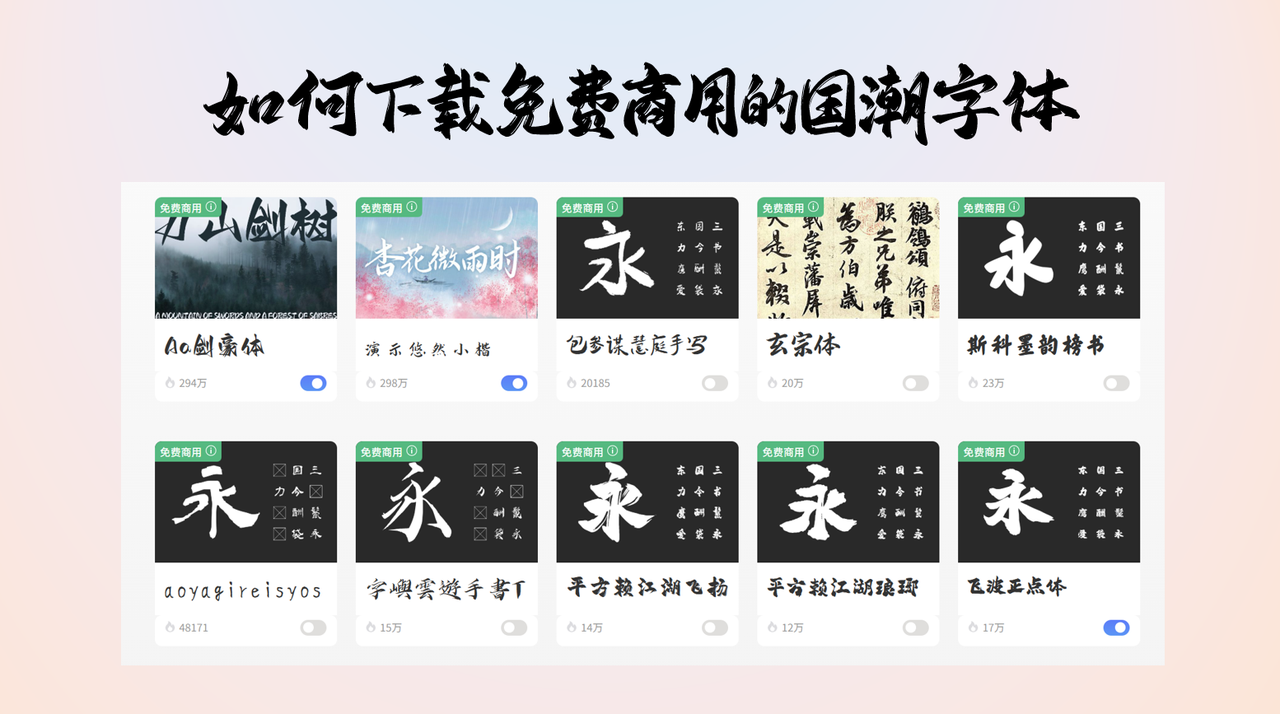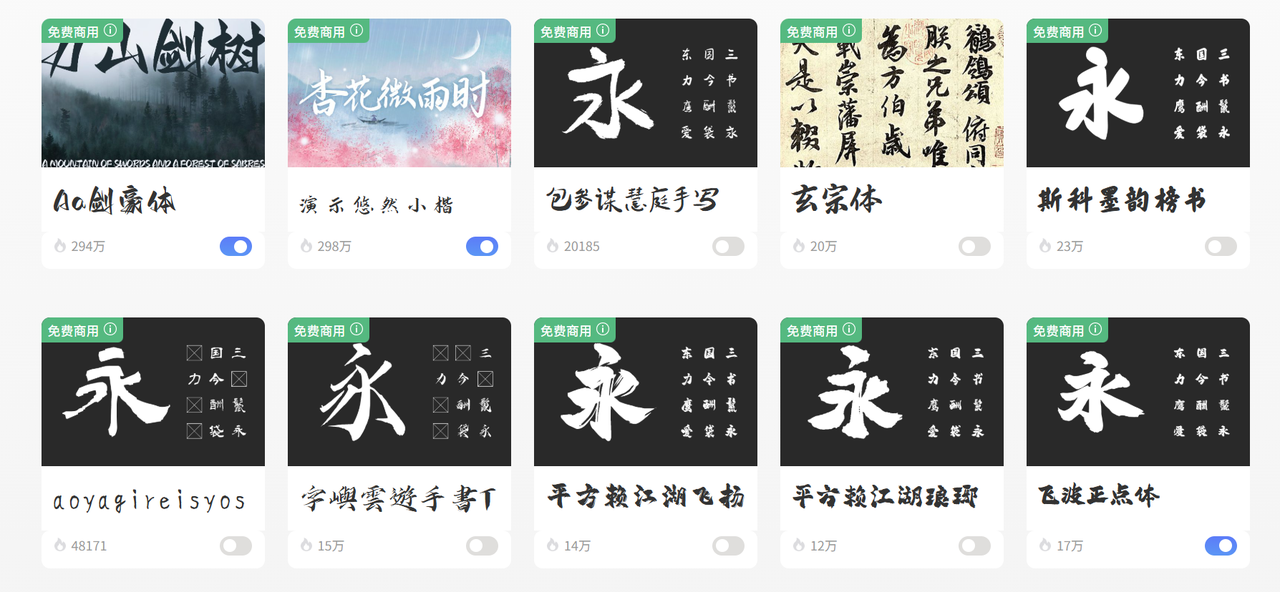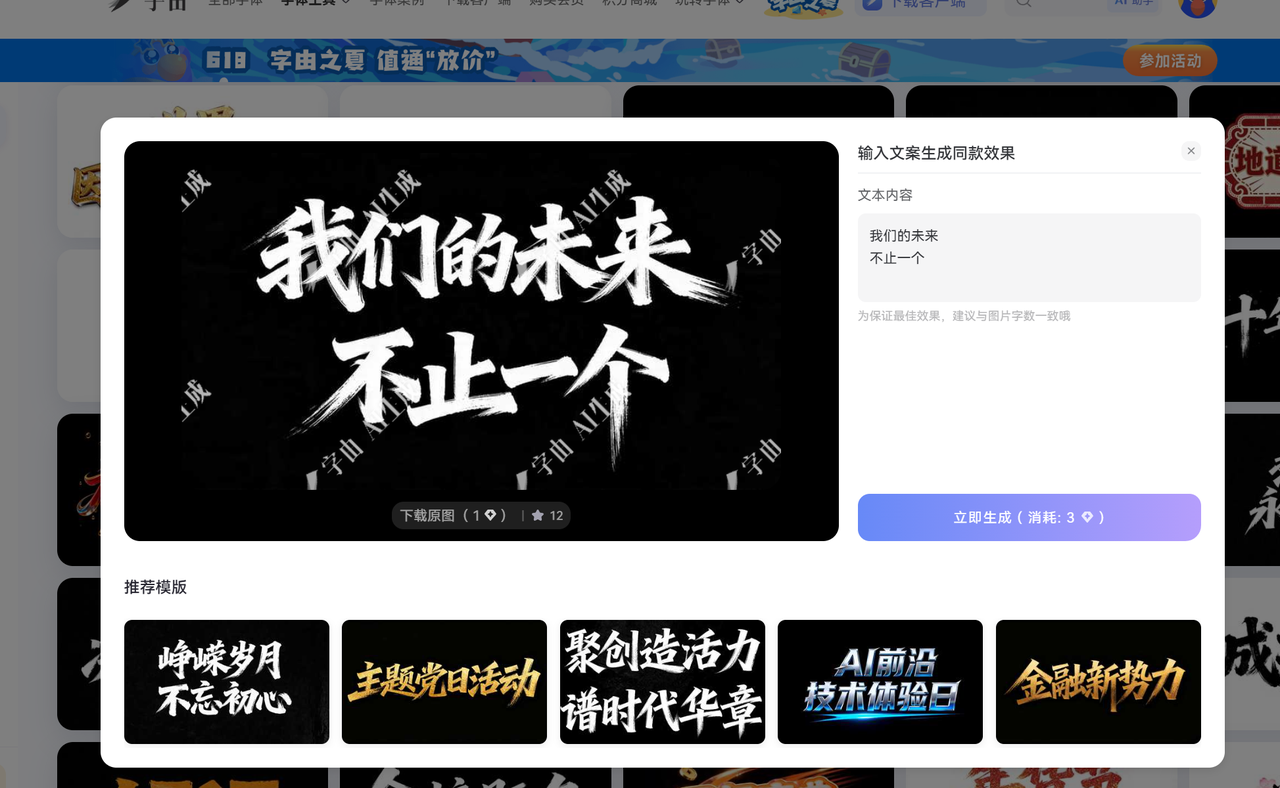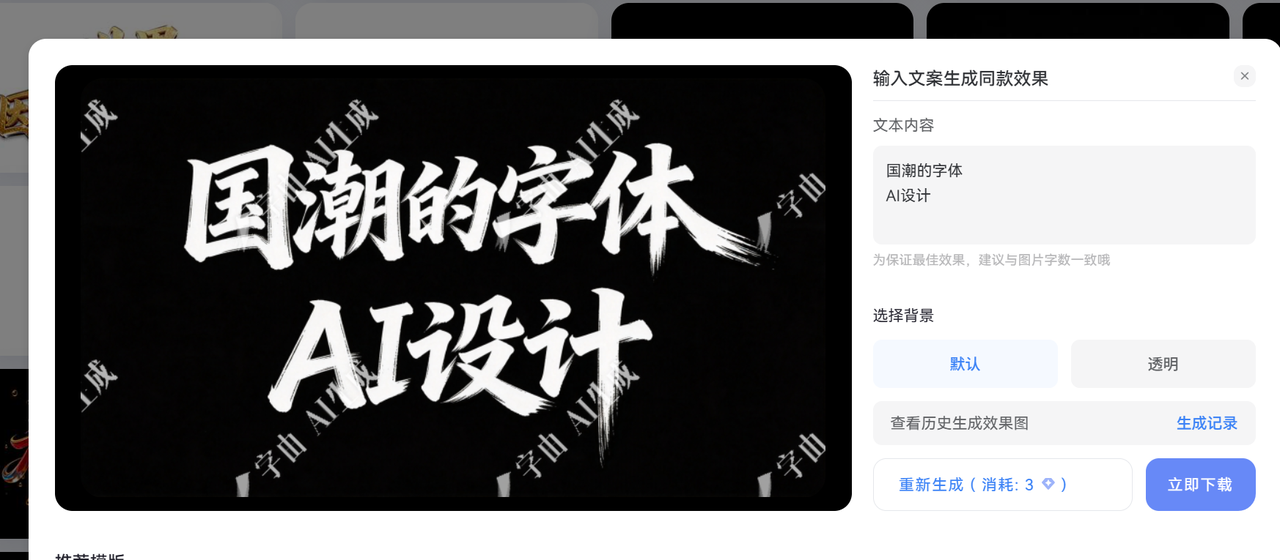
如何下载免费商用的国潮字体,教你这两个方法
“国潮”风格在这几年火遍大江南北,从奶茶包装到手机发布会,随处可见苍劲有力的书法、厚重拙朴的魏碑。但问题也随之而来:高质量的国潮字体往往价格不菲,本篇文章,我会毫无保留地分享我近期发现的免费商用的国潮字体下载的方法,以及如何通过 AI 在线完成国潮字体设计和下载。
你会发现,字由整合了市面上绝大多数的高质量开源字体(如思源系列、站酷系列),同时还有很多独立设计师授权给字由平台免费使用的精美字体。这些字体在保持中式韵味的同时,排版效果非常稳定。
1. 如何用字由 AI 生成国潮字体
字由上线的 AI 字体,为国潮字体的设计和下载,提供了更方便的方式。以前我们做国潮字体,如果现成的字体不满意,需要自己去设计软件中一个笔画一个笔画地拉锚点。通过字由的 AI 功能,你可以使用 AI 直接生成。